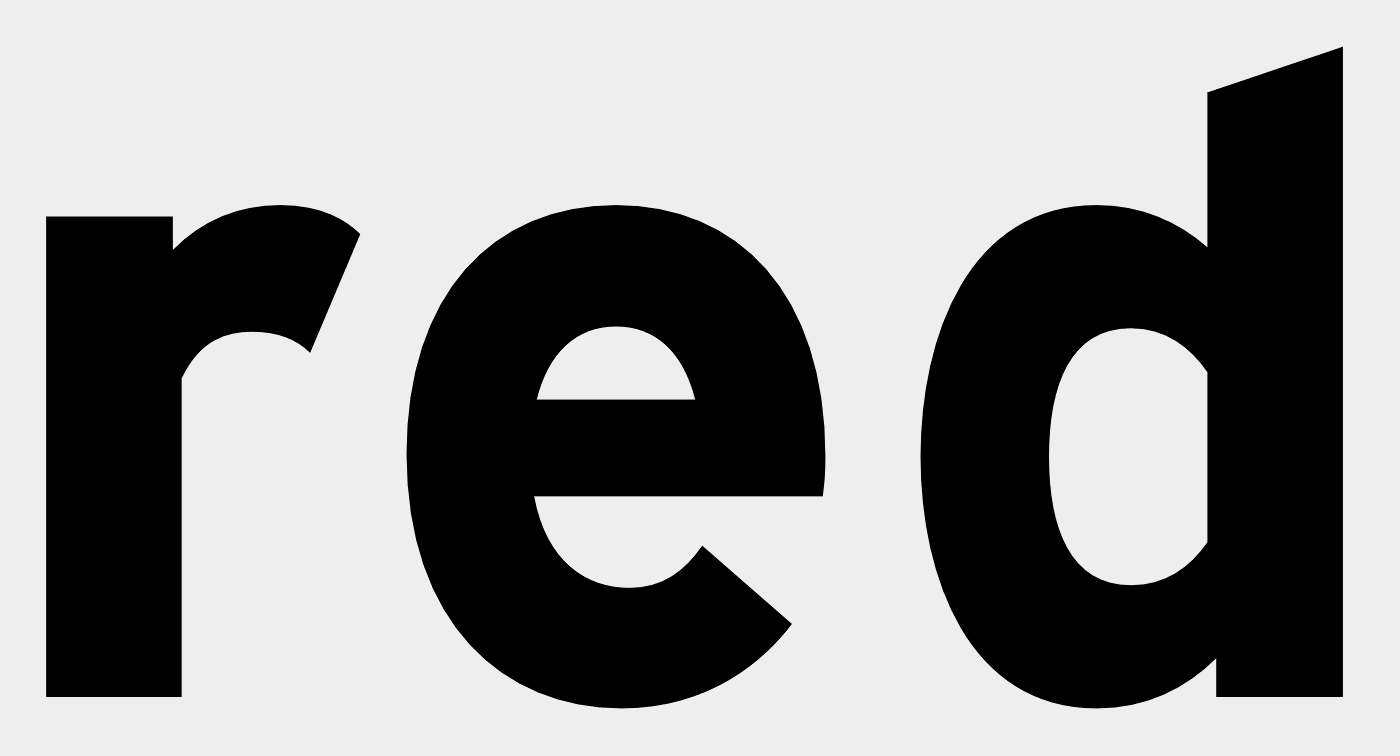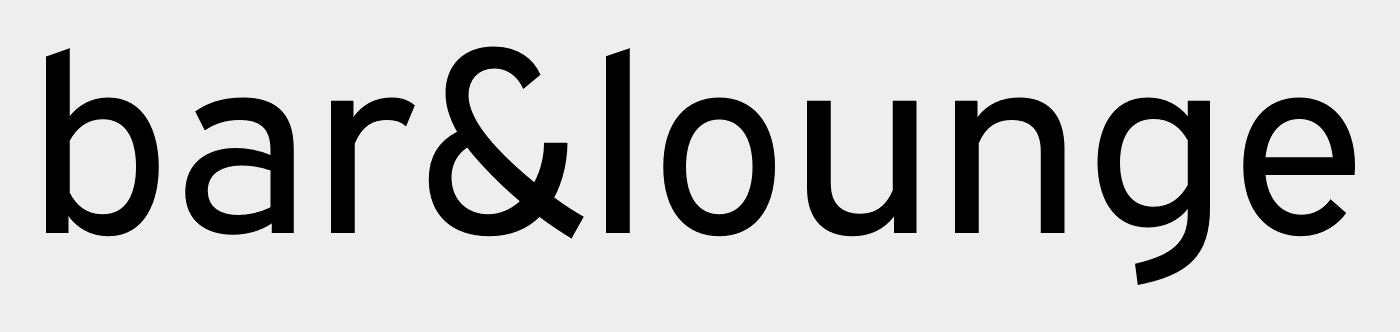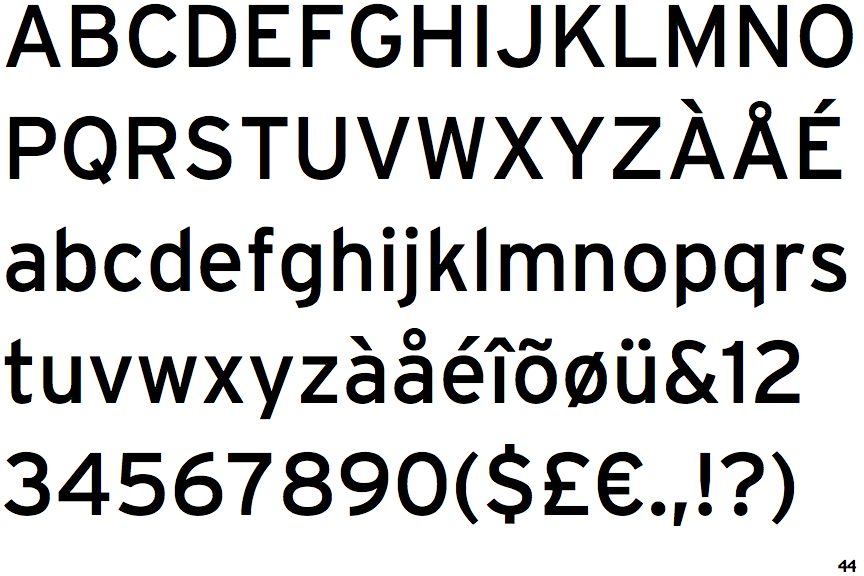
Ich suche die Schriftart dieses Logos
ich hoffe ihr könnt mir helfen, ich benötige dirngend die Schriftart von diesem Logo.
Interstate Bold.
das ist eine FHWA-Series Schilderschrift aus den USA. FHWA-> Federal Highway Administration. Davon gibt es verschiedene Digitalisierungen.  Hier mal die Expressway von Ray Larabie.
Das ist aber die falsche Digitalisierung, siehe das &.  Aber dort findest Du interessante Informationen über die Schrift als solches. Bei Myfonts findet man unter Interstate nichts, aber bei Identifont sieht es besser aus. Die Frage nach der Interstate:
liefert das passende &:
Interstate
Based on the lettering used on the signs of the United States Federal Highway Administration.
Designer: Tobias Frere-Jones
Year: 1993-99
Copyright: Font Bureau
Publisher: Font Bureau
Part of a family that offers an exceptionally wide range of weights and/or styles.